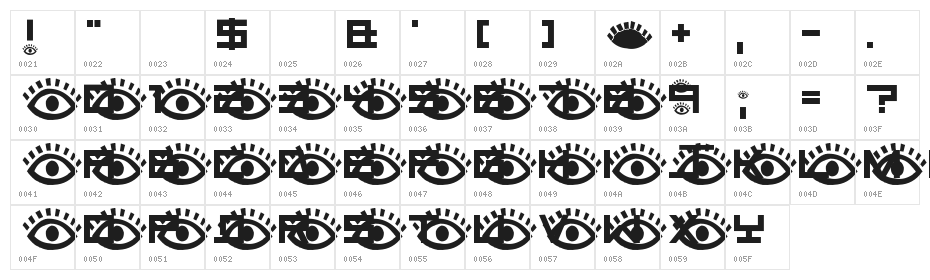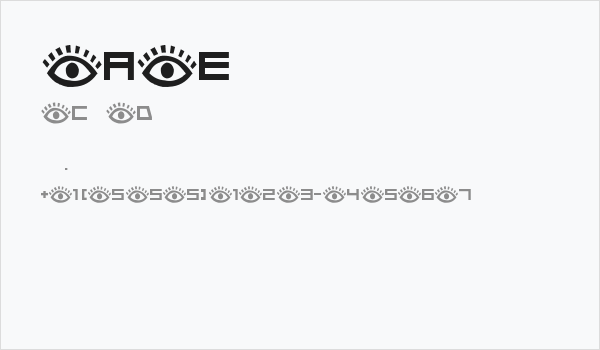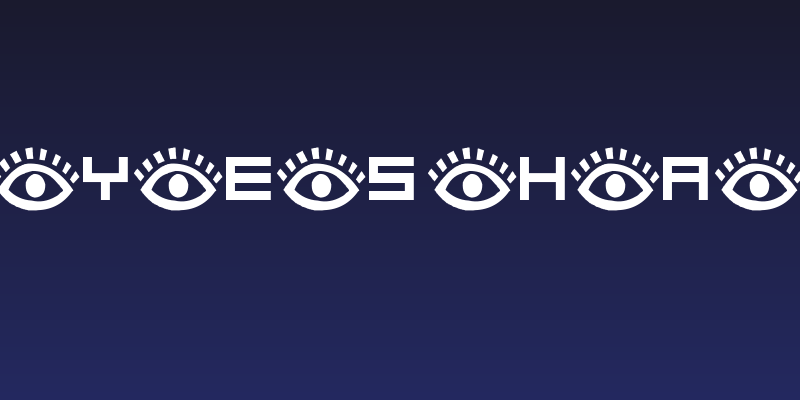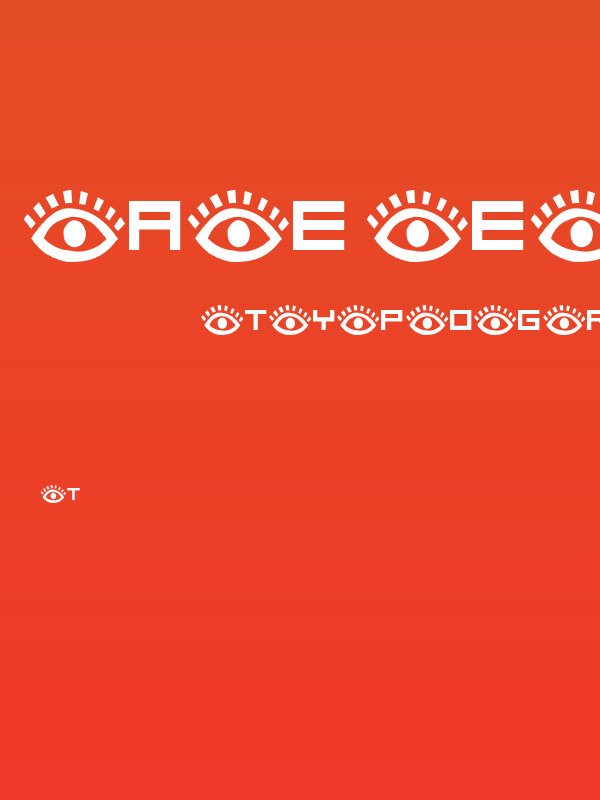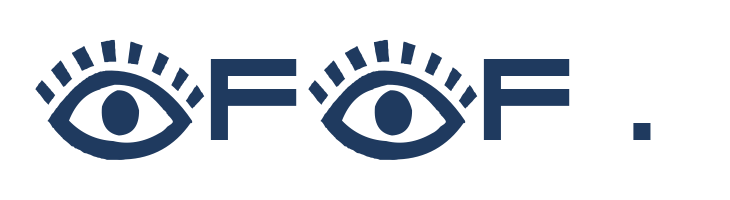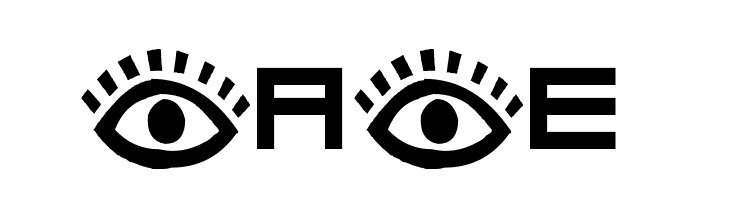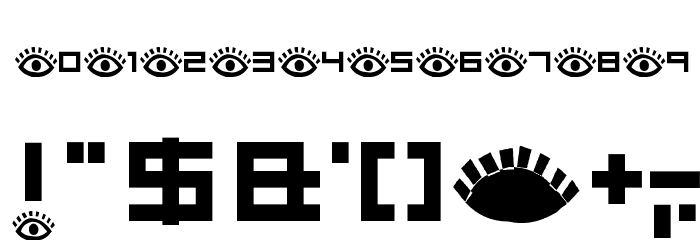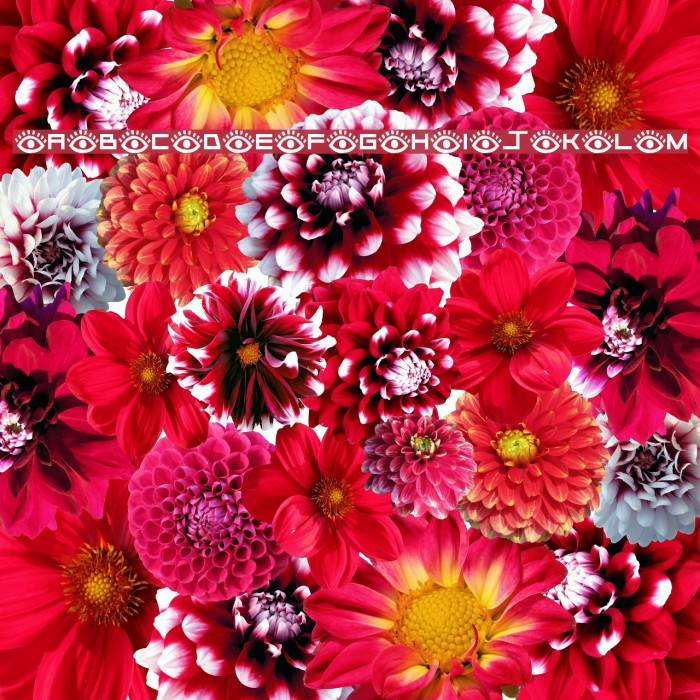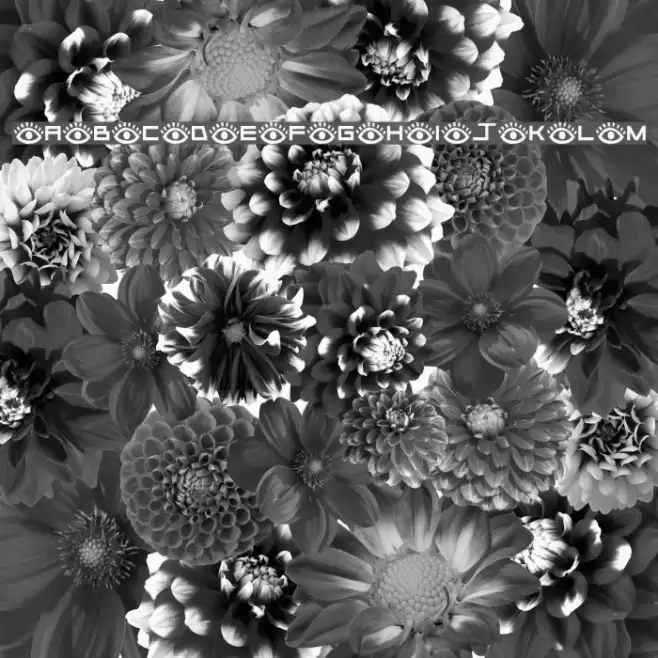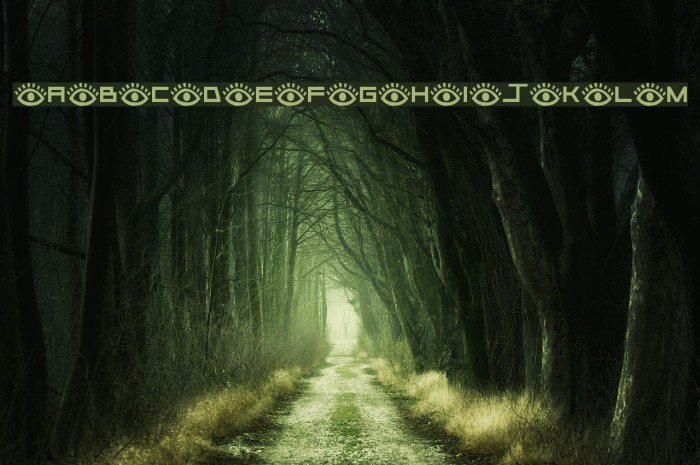
AEZ eyes have it Font
| Caso de uso | Logos, Posters, Artistic Branding |
| Proyectos propuestos | Ideal for creative projects such as posters, album covers, branding for artistic ventures, and any design work that benefits from a unique and eye-catching typeface. |